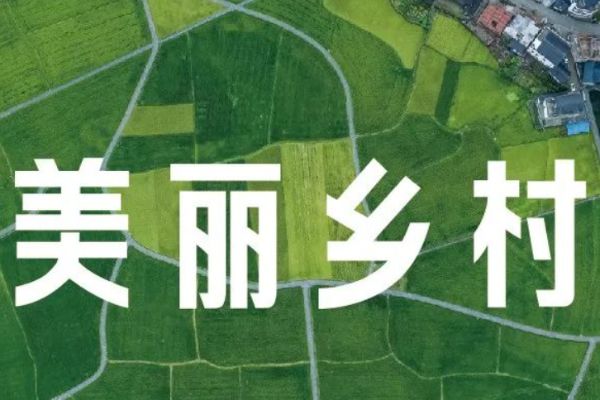
乡立方黑体
乡立方黑体是一款主打简约风格的创意字体,支持简体中文常规字符集,授权范围为免费商用,为设计师提供高性价比的用字选择。 这款字体在字形结构上兼具稳定与巧思:整体形态方正大气,字体重心居中,中宫松紧适中,既保证阅读时的视觉平衡,又避免过于紧凑的压迫感。笔型设计尤为亮眼,采用利落直角线条,笔画以方头收尾,粗细均匀的笔触搭配部分笔画断开处理,打破传统黑体的沉闷,赋予字体独特的设计张力——稳重中透着灵动,简约里藏着细节。 作为免费商用字体,乡立方黑体适配多种设计场景:品牌标题、包装文案、新媒体海报等场景中,其方正利落的字形与个性笔画设计,能快速抓住视觉焦点,让信息传递更具记忆点,是兼顾实用性与创意性的优质用字选择。